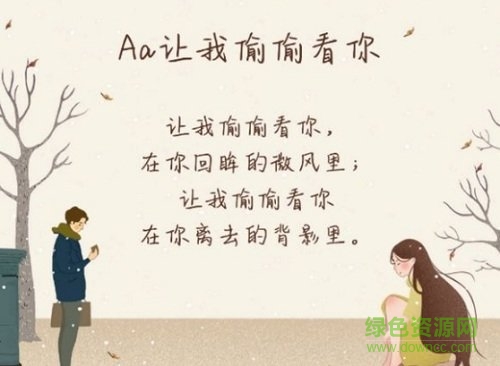
aa讓我偷偷看你字體ttf是字體管家推出的一款干凈溫潤(rùn)的手寫(xiě)字體,可以用作表白、手機(jī)字體展示等,有著舒適的閱讀體驗(yàn),需要的朋友就來(lái)綠色資源網(wǎng)下載吧!
aa讓我偷偷看你也叫作Aa偷偷喜歡你,設(shè)計(jì)理念是:我已經(jīng)偷偷喜歡你好幾個(gè)星期五了。這是一款十分浪漫、感動(dòng)的戀愛(ài)字體,給你獨(dú)特心動(dòng)體驗(yàn)!
aa讓我偷偷看你體字庫(kù)完整,不僅支持繁簡(jiǎn)體中文,還支持日文使用,很能滿(mǎn)足設(shè)計(jì)師們的要求,在文字設(shè)計(jì)、藝術(shù)設(shè)計(jì)、平面設(shè)計(jì)效果更加出色!